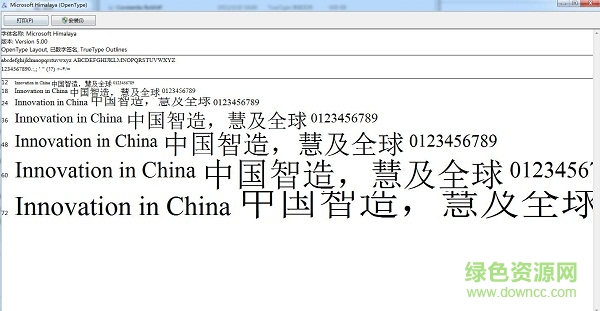
microsoft himalaya
microsoft himalaya字體是一款windows系統(tǒng)襯線字體,同時(shí)也支持for mac系統(tǒng),線條纖細(xì)均勻,排印清晰,整體結(jié)構(gòu)張弛有序,小編為大家整理了安裝步驟,歡迎下載體驗(yàn)!
襯線字體特點(diǎn)
serif字體在字符筆畫(huà)末端有叫做襯線(serif)的一些小細(xì)節(jié)。這些細(xì)節(jié)在大寫(xiě)字母中特別明顯。serif字體包括Times New Roman、Georgia和Palatino等。